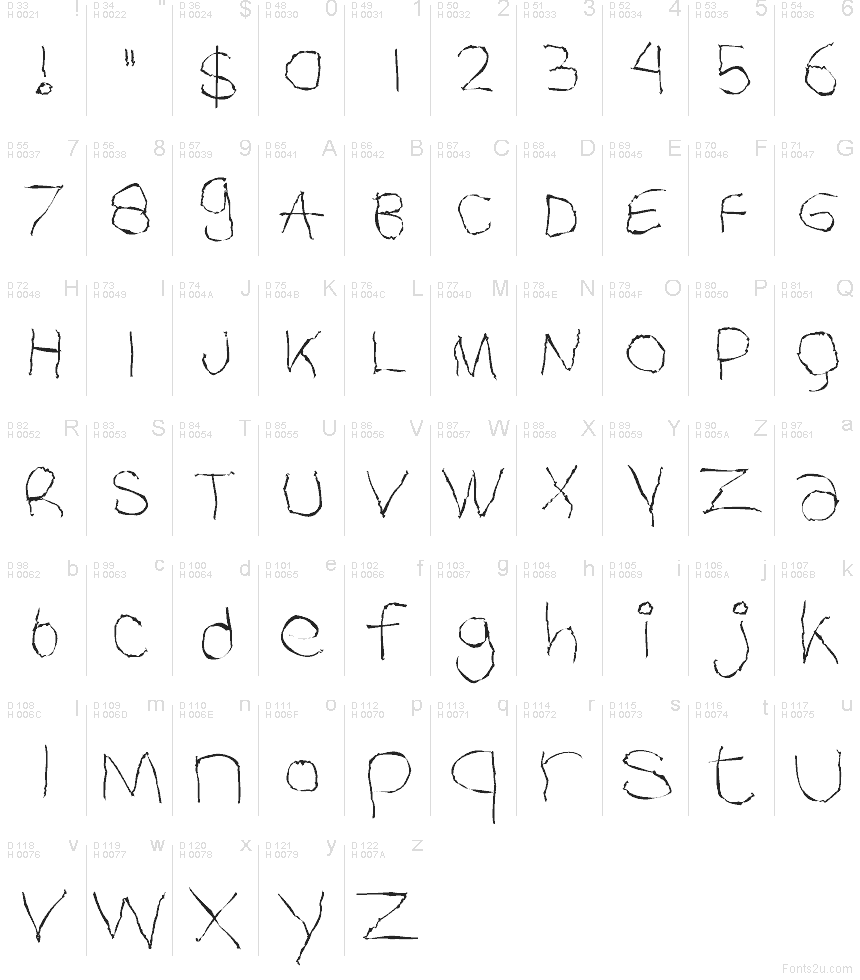
Comma Write, který navrhl Ffeeaarr, je bezplatné rukou psané titulkové písmo s vysokými, kolísavými kapitálkami a záměrně nestabilní obrysovou linkou. Zaoblená písmena vypadají volně nakreslená a ostré vrcholy a dlouhé diagonály dodávají písmu nervózní, škrábavý pohyb.
Jeho drsné kontury mohou připomínat ručně kreslené bytosti a netradiční ilustrace v dětské literatuře nebo herní grafice. Písmo se hodí také na hudební plakáty postavené na surové, domácké estetice. U propagačních letáků a obálek nezávislých časopisů se může stát součástí samotného uměleckého díla, jako narychlo vytvořená jmenovka nakreslená přímo na obrázku.